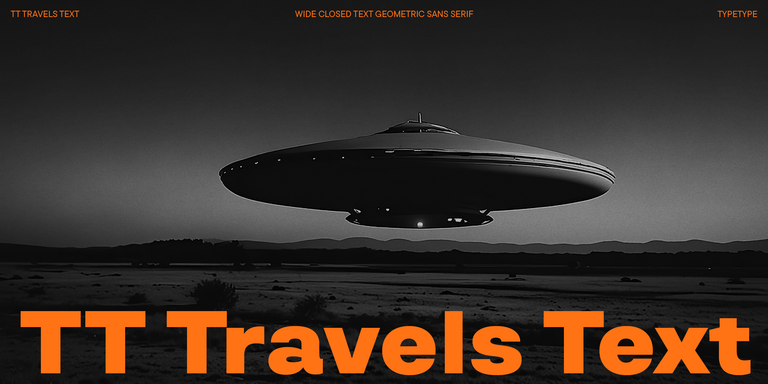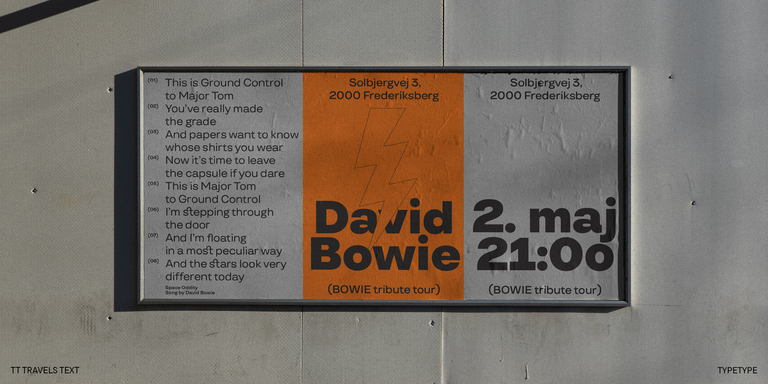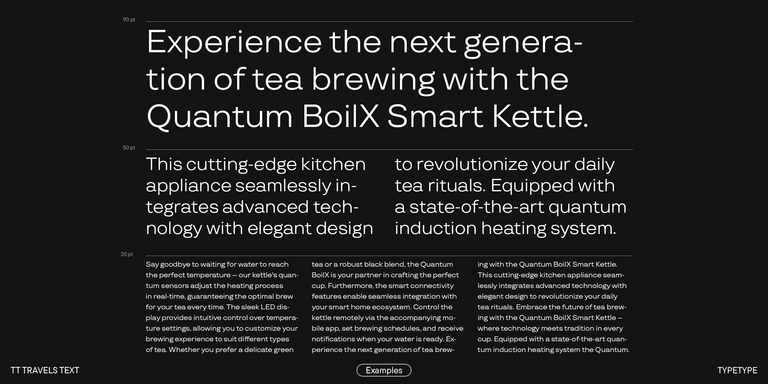
TT Ramillas es una fuente con serifas elegante y contemporánea que eleva el diseño a la categoría de arte. Caracterizada por sus estilos decorativos únicos y capitulares con ornamentos florales, crea experiencias visuales realmente únicas. Ya presente en más de 3000 sitios web en todo el mundo, ha sido galardonada con el premio Modern Cyrillic y redefine la sofisticación tipográfica.
TT Bluescreens es una sans serif geométrica mejorada con proporciones estrechas.
TT Severs es una sans serif geométrica con elementos internos enfatizados. La principal característica visual de TT Severs es la forma inusual de sus óvalos interiores.
TT Quaris es una exquisita sans serif moderna de alto contraste cuyo diseño equilibra suavidad y nitidez. Las formas de los glifos son fluidas y tienden a la redondez, aunque también incorporan elementos afilados.
TT Bakers es una serif fluida con un carácter suave y vivaz. Esta tipografía recuerda a la repostería recién horneada: cálida y blanda, especialmente en sus pesos más gruesos.
TT Ramillas es una serif contemporánea con gran versatilidad editorial. Incluye estilos decorativos e iniciales ornamentales con motivos florales.